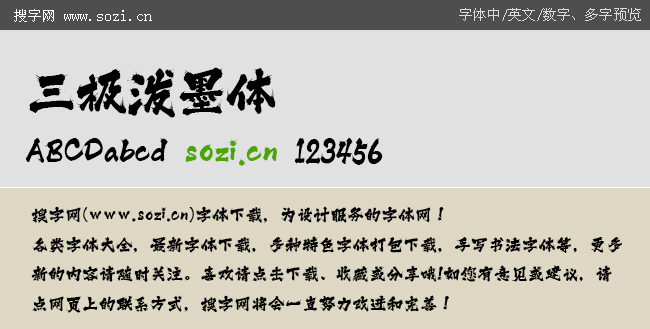
三極潑墨體
搜字網(wǎng)給大家提供一款三極潑墨體中文字體下載,三極潑墨體是一款手寫風(fēng)格的書法字體,字體瀟灑大方,筆鋒勁現(xiàn),視覺效果非常不錯(cuò)。適用于平面宣傳設(shè)計(jì)、網(wǎng)頁設(shè)計(jì)、海報(bào)設(shè)計(jì)等應(yīng)用。